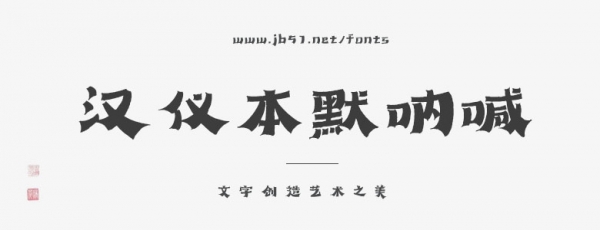
漢儀本默吶喊是漢儀字庫簽約作者本默(王琪)創(chuàng)作的一款風(fēng)格怪誕的手寫字體,夸張而極具裝飾性。這款字體源于作者在一次海報創(chuàng)作中的偶然嘗試,是在宋體和黑體的基礎(chǔ)上進(jìn)行再次創(chuàng)作的美術(shù)字體,整體以扁平化為基調(diào),結(jié)合板書的設(shè)計呈現(xiàn),具有視覺沖擊力和極高的辨識度,奪人眼球,適合作為標(biāo)題字體滿足多種應(yīng)用場景。